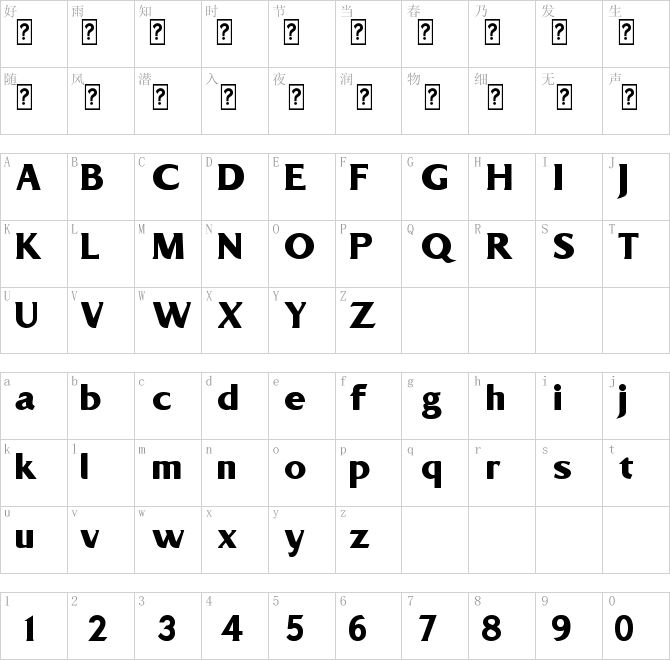
Upward Bold
Upward Bold是一款不错的英文字体。
字体简介:
本字库设计创作灵感来自中华名族传统文化中的太极中心思想的“柔中带刚,随机应变”,字库字体在视觉上体现出了“刚正亦圆滑”的特征。本字库的核心思想是“柔中带刚,随机应变”寓意着对生活与事物积极向上的态度。
本字库字体采用封闭式结构,笔画字骨采用直挺为主架构,字体轮廓1/4采用弧角设计,字体整体在视觉上体现出既直挺平滑又圆润。本字库取名为《华司向上体》英文名为《Upward》当前总计字符有241个,字符分别有:基本拉丁字母、拉丁字母补充、拉丁字母扩展、间距修饰符号、希腊字母和科普特字母、常用标点15个、货币符号4个、字母式符号2个、数学运算符、私用区(字母表达形式)、半角和全角。
字体名称:华司向上体
字体风格:Upward Bold
字体全称:华司向上体 Bold